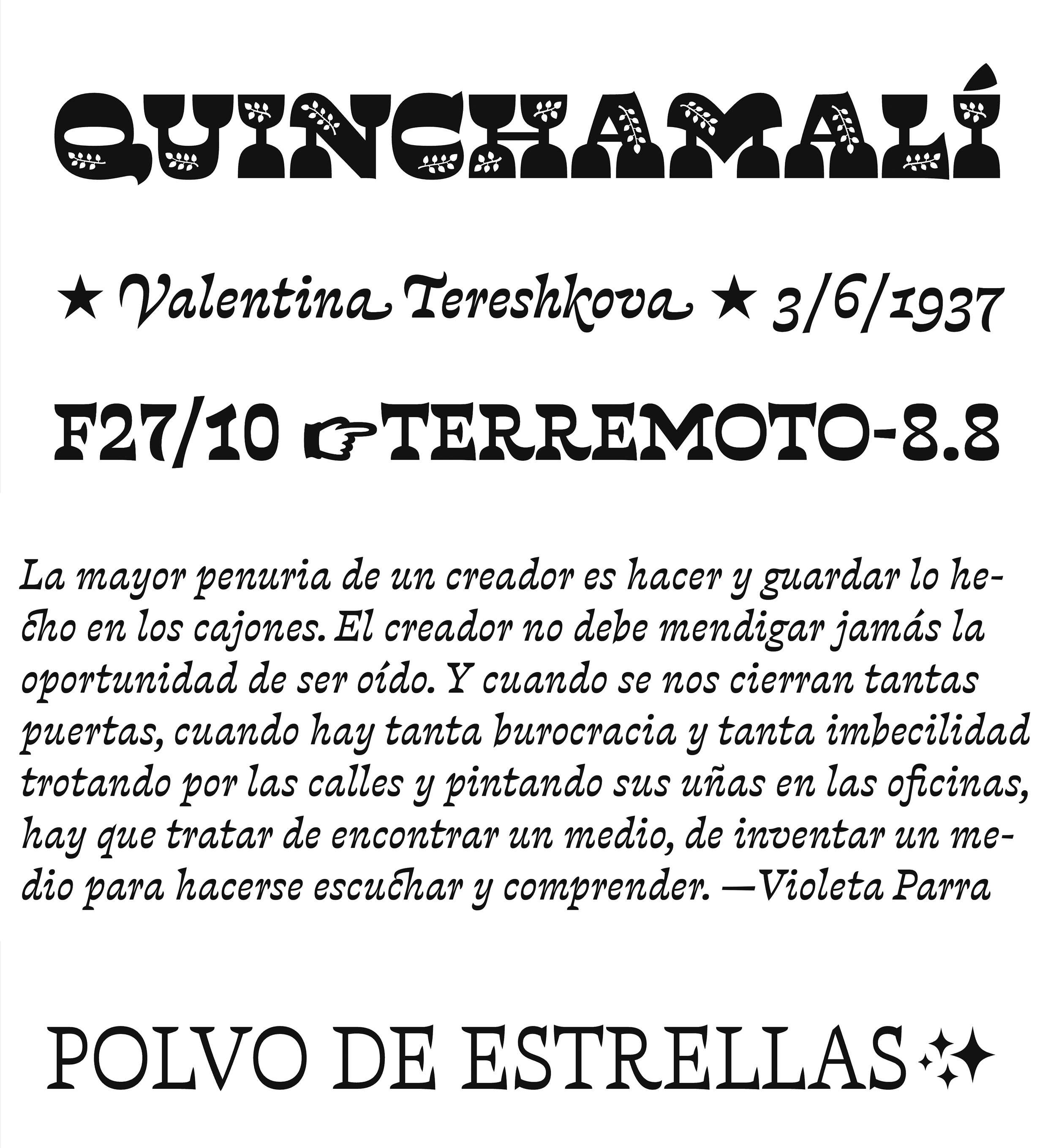
| Año | 2007 — Actualizada: ( 2023 ) |
| Créditos | Javier Quintana |
| Descripción | Violeta es una tipografía diseñada para texto, compuesta por seis grosores en estilos romano e itálico, además de una mayúscula iluminada. Su principal característica es su marcado contraste inverso, una característica que, sin duda, no se considera para la composición tipográfica de textos largos. Violeta ha evolucionado lentamente, sin ansiedad, completamente ajena a las modas ni a las tendencias pasajeras del diseño desechable. Violeta cuenta con numerosas funciones OpenType, que permiten acceder a versalitas, varios tipos de cifras, glifos alternativos, conjuntos estilísticos y otras mejoras tipográficas. |
| Clasificación | Texto, Títulos, Dingbats |
| Familia(s) | Libro, Libro en cursiva, Regular, Cursiva regular, Mediocursiva, media Seminegrita, Seminegrita cursiva, Atrevido, Negrita cursivaNegro, Cursiva negra, Jardinera |